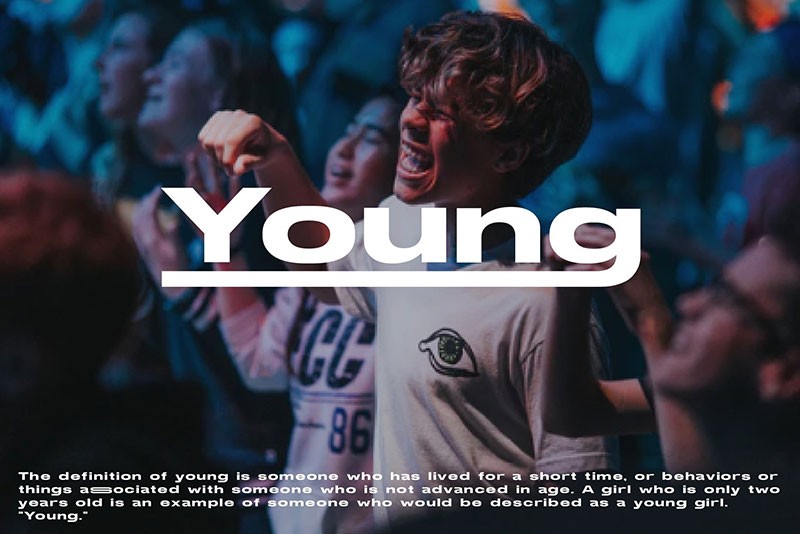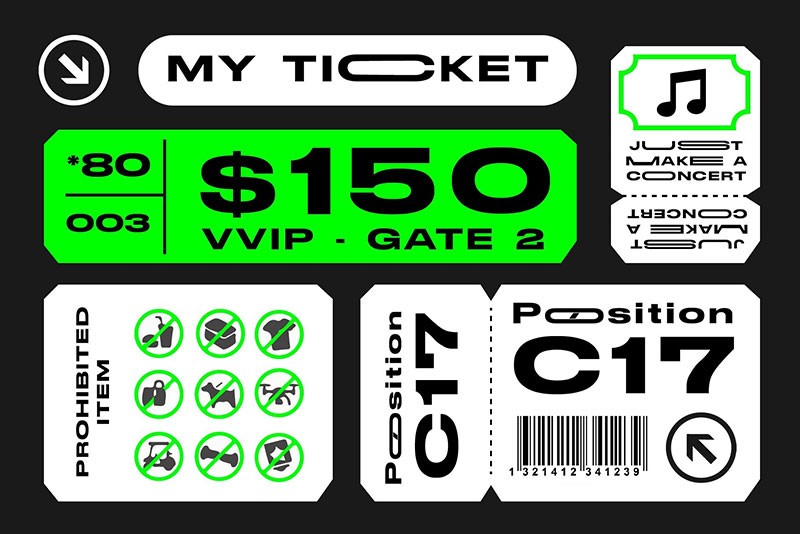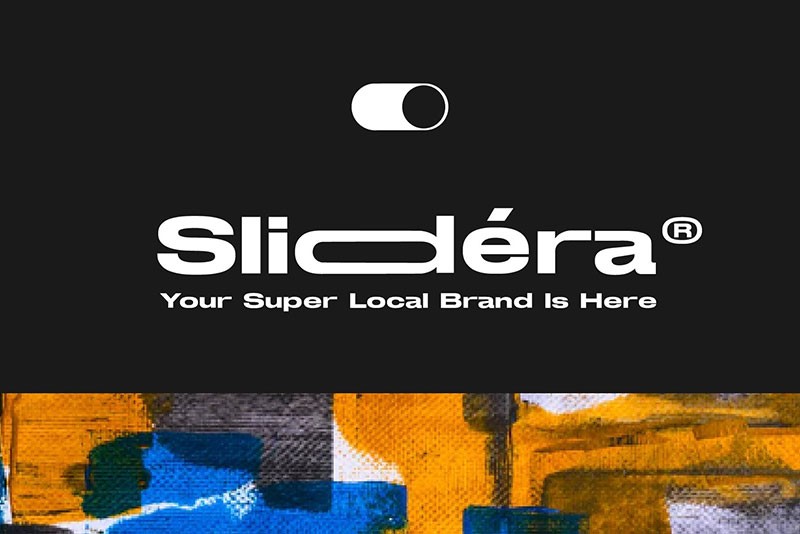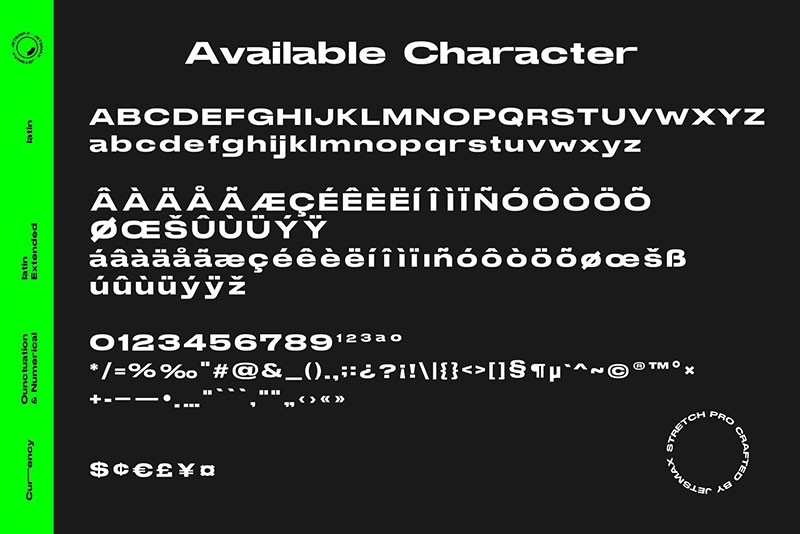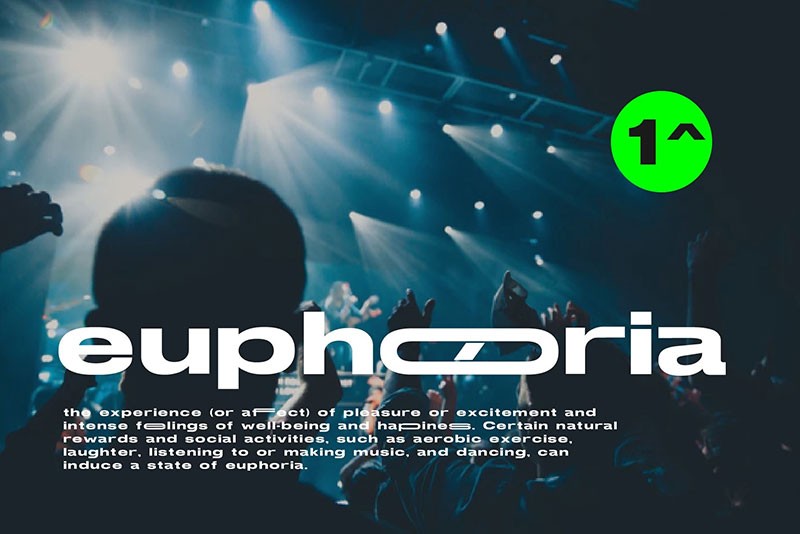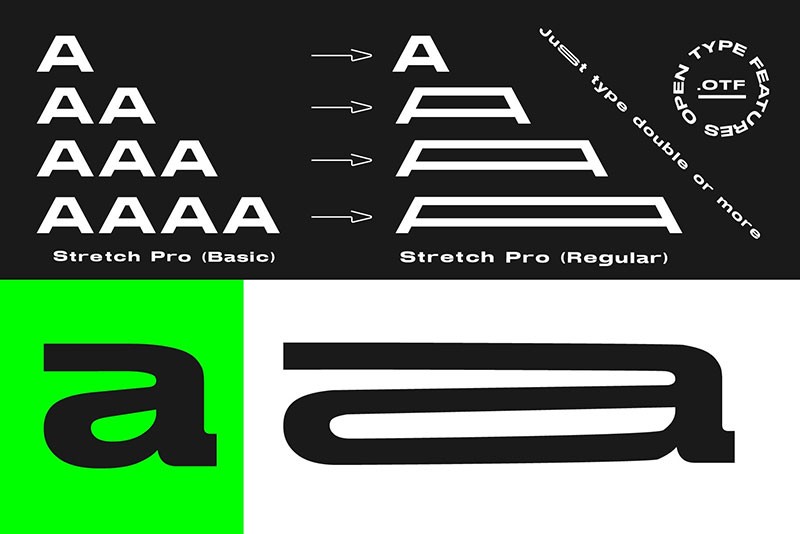
Stretch Pro可拉伸无衬线英文字体
StretchPro是一款非常酷炫的无衬线字体,其创意拉伸设计使其非常适合于未来主义和现代主题。这种字体具有独特的外观和动感,能够为您的设计带来前卫和现代的氛围。
拉升效果的使用方法说明如下:
• 输入相同的三个字母,例如"AAA"或"BBB"。
• 根据输入的字母个数,StretchPro字体会自动将每个字母进行拉升。
• 拉升的长度将根据输入的字母个数而变化。例如,输入"AAA",每个字母都会被拉升以创建一个更长的外观。
• 注意,StretchPro字体最多支持三个字母的拉升效果。输入更多的字母可能不会产生拉升效果。
通过使用拉升效果,您可以为文本添加一种独特的变形和引人注目的视觉效果。这可以用于突出重要的文字、标题、标语或设计元素,以吸引观众的注意力,并为您的设计带来一份现代和创意的感觉。